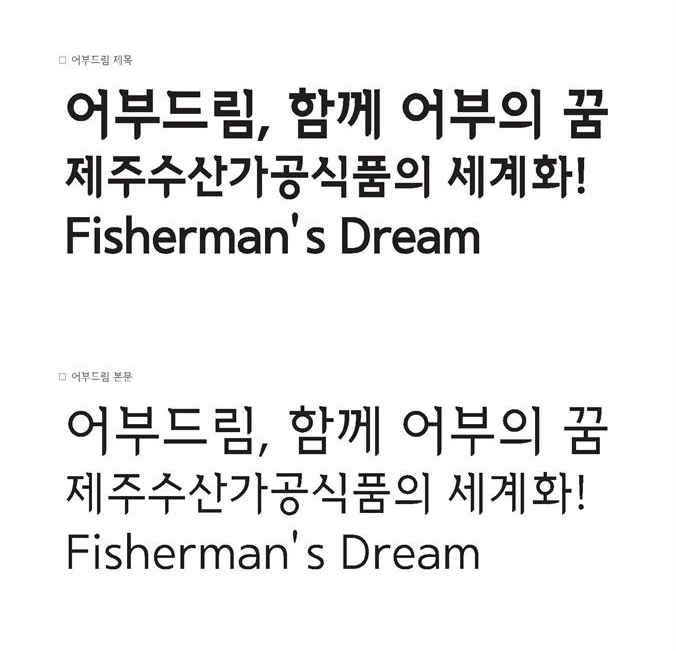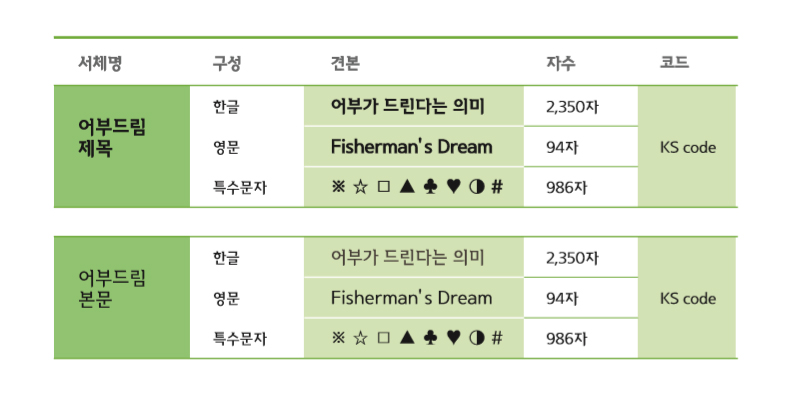
제주씨푸드RIS사업단, 어부드림 폰트 무료 배포
제주씨푸드RIS사업단이 제주 수산물 공동브랜드 ‘어부드림’의 확산을 위해 ‘어부드림’ 전용 폰트를 개발하여 무료 배포한다.
어부드림은 제주 지역 수산물의 공동 브랜드로, 산업통상지원부의 지원을 받아 제주 국제대학교 제주씨푸드RIS사업단이 개발했다. 제주 수산물 기업을 대상으로 보급하여 제주 수산물의 경쟁력 강화에 힘을 보태고 있다. 어부드림 전용 폰트 또한 이러한 브랜드 경쟁력 강화의 일환으로 개발되었다. 브랜드 이미지, 상징성, 고유성 등을 살리면서 제주 수산식품의 격을 높일 수 있는 디자인적 특징을 갖추고 있다.
어부드림 전용 폰트는 고딕의 형태를 띄고 있으며 어부드림 이미지와 소비자와의 연상 이미지를 토대로 심플하고 기하학적인 형태의 이미지를 서체로 표현하였다. 사용자는 용도에 따라 획의 굵기가 다른 제목용, 본문용 서체를 구분하여 사용할 수 있으며, 프리 라이선스로 배포하고 있어 누구나 자유롭게 사용할 수도 있다.
제주씨푸드RIS사업단은 이번 어부드림 폰트의 무료 배포를 통해 수산물 브랜드에 대한 젊은 소비자들의 관심을 끌고, 긍정적인 인식 형성에 도움을 줄 수 있을 것으로 기대하고 있다. 또한 향후에도 어부드림 브랜드를 육성하기 위한 다양한 마케팅 활동을 진행할 계획이라고 밝혔다.